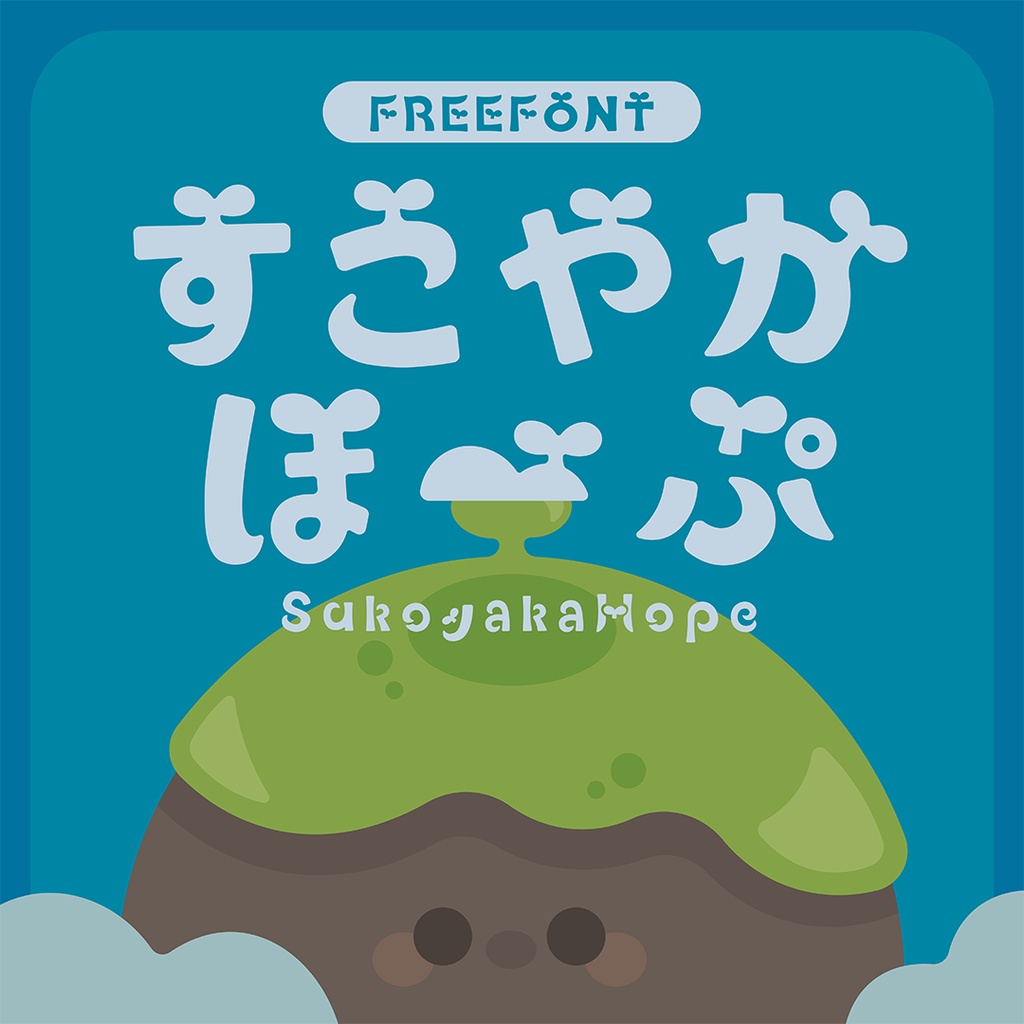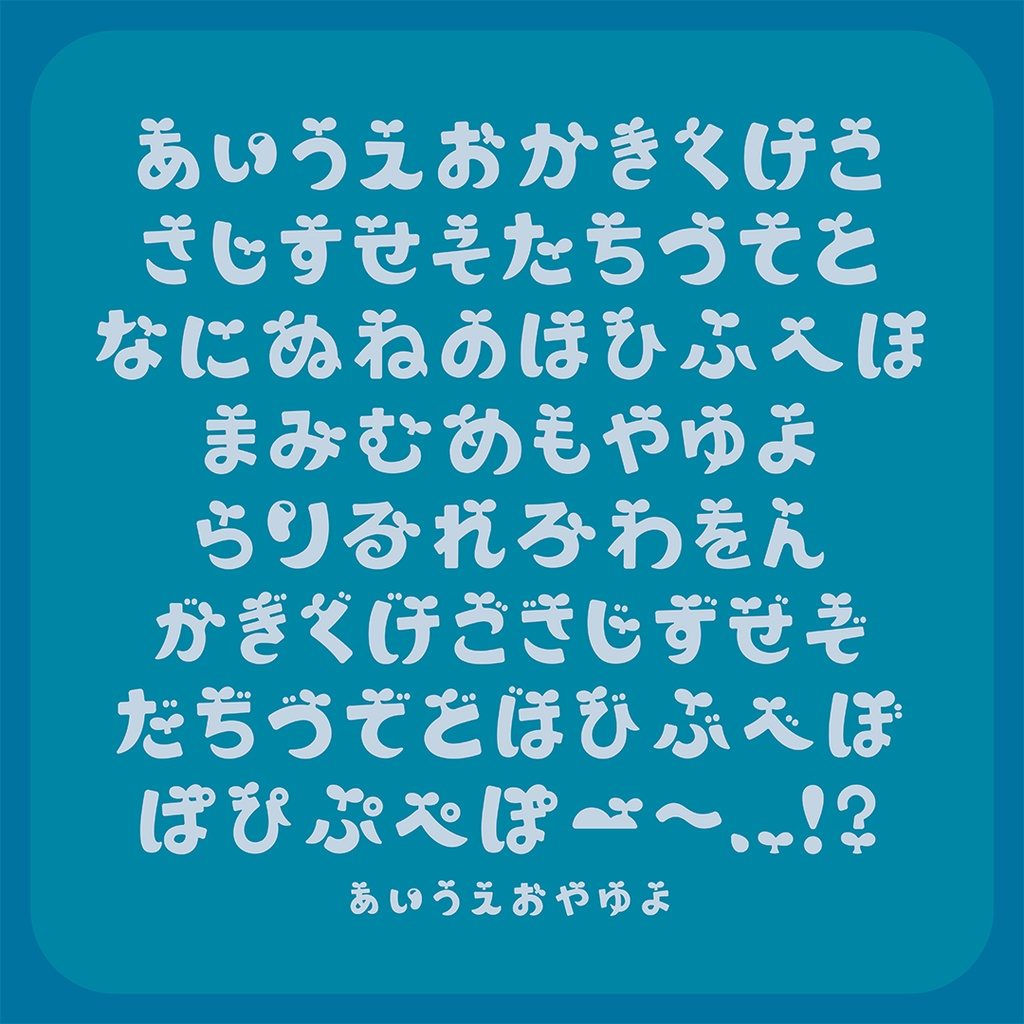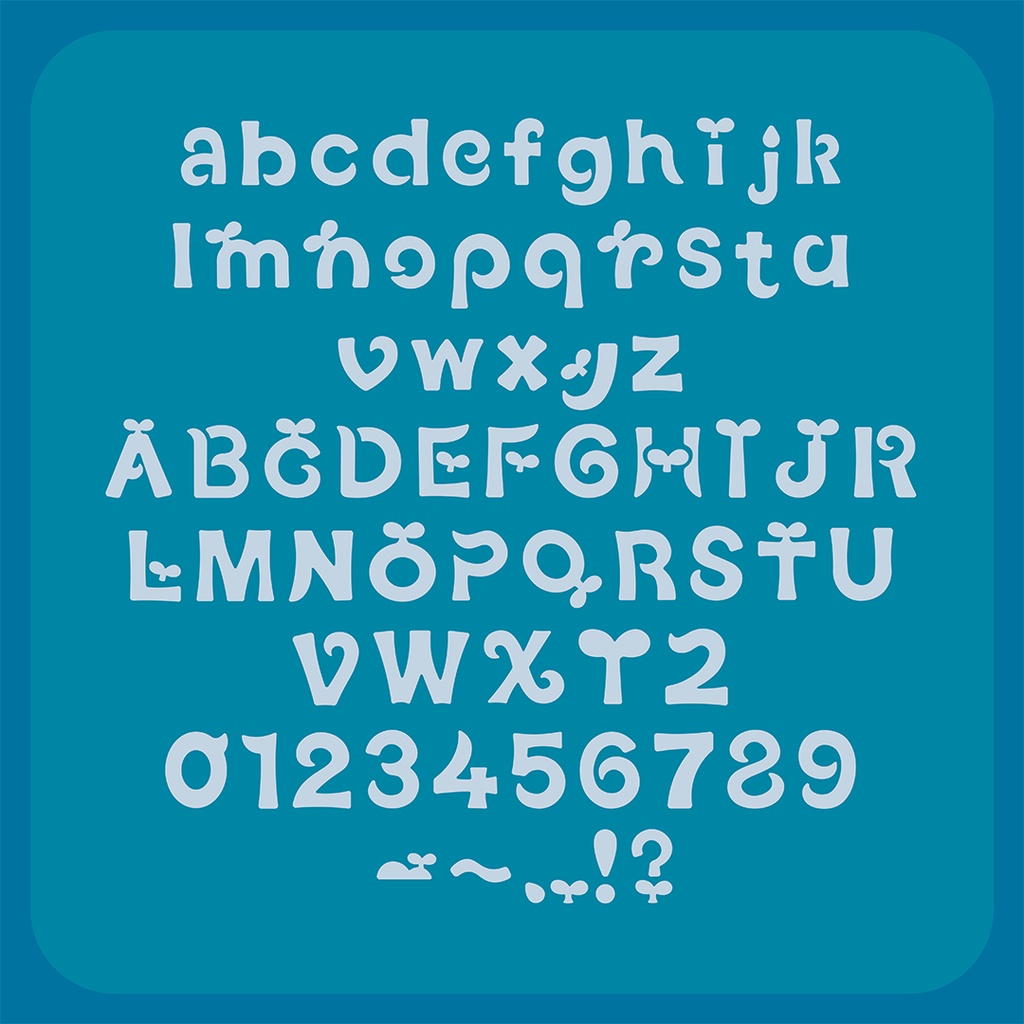
すこやかほーぷ(フリーフォント)
◯当フォントについて 「すこやかほーぷ」は、双葉をテーマにしたオリジナルフォントです。 健やかに生きていけますようにという前向きな願いを込めたものとなります。 収録文字:ひらがな、アルファベット、数字、一部記号 フォントデータ形式:OpenType ◯利用にあたって この商品はフリーフォントです。 個人商用問わず無償で使用することが可能です。 デザインに合わせた変形や加工も自由にしていただいて大丈夫です。 また当フォントを再配布、公序良俗に反した用途での使用はお控えください。 当フォント使用時に生じたトラブル等に関して、一切の責任を負いかねます。 ◯最後に 当フォントは、製作者が初めて作ったフォントとなります。 基本的な使用は出来るように、なるべく調整はしておりますが、 一部パスの甘さや字間等の調整不足が残っている可能性があります。 今後の更新で改善をしていけるようにと考えておりますが、 現バージョンの至らない点に関してご了承いただけますと幸いです。 ◯最終更新日 2026年4月10日